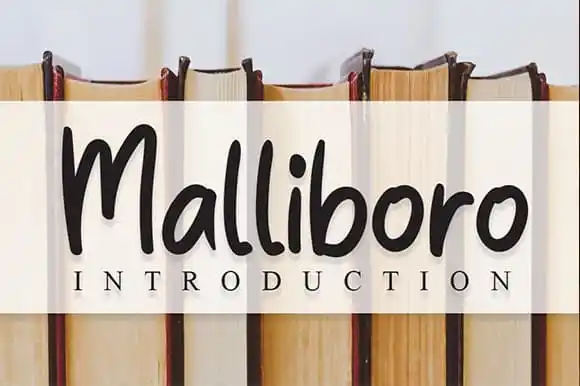
Malliboro Script Font – Download Grátis
Malliboro Script Font é uma elegante serif que surge para dar vida a projetos criativos em formato texto. Suas linhas delicadas e detalhes meticulosamente cuidados garantem um estilo único, perfeito para adicionar um toque de sofisticação em diversas aplicações gráficas. Seja para personalizar postagens no Instagram, criar logotipos para marcas sociais ou mesmo decorar embalagens de produtos, esta fonte possui a capacidade de se adaptar a inúmeros usos sem perder seu charme especial. A designer andikastudio desenvolveu este projeto, focando na necessidade de uma fonte com estilo próprio que possa ser utilizada em diferentes cenários do mercado visual. Desde embalagens de produtos até cartazes publicitários, Malliboro Script é uma opção ideal para aqueles buscando uma fonte que transmita sofisticação e personalidade. Além disso, a sua perfeita harmonia entre linhas e espaçamentos faz dela um recurso indispensável em qualquer trabalho que exige o toque delicado de uma mão humana no papel.